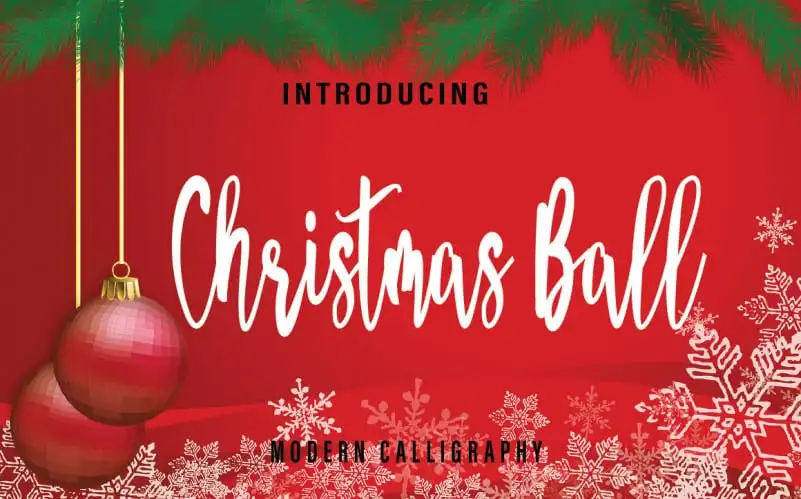
Christmas Ball Script Font – Download Grátis
A Fonte ‘Christmas Ball Script’ é uma elegante escolha para personalizar seu projeto natalício com a delicadeza do traçado manual. Nesta categoria especial de Fonts de Escrita, você encontrará um toque criativo que enriquece seus trabalhos de Natal. Este font é perfeito para aqueles projetos de aniversário e celebrações natalinas onde deseja adicionar aquela pitada especial de charme. Com o ‘Christmas Ball Script Font’, suas criações ganham vida, tornando-se ainda mais únicos e personalizados. Perfeito tanto para pequenos detalhes quanto para design em grande escala, esta font é uma ótima escolha para qualquer projeto natalino que deseje destacar a sua criatividade. A cada traçado da ‘Christmas Ball Script Font’, você pode sentir o carinho e dedicação do designer Farz Studio. Este designer nos oferece um toque de natureza no seu trabalho, fazendo deste font uma escolha única para aqueles projetos que exigem personalização e estilo. Com esse font à mão, transforme suas celebrações natalinas em verdadeiros momentos de criatividade e festa!